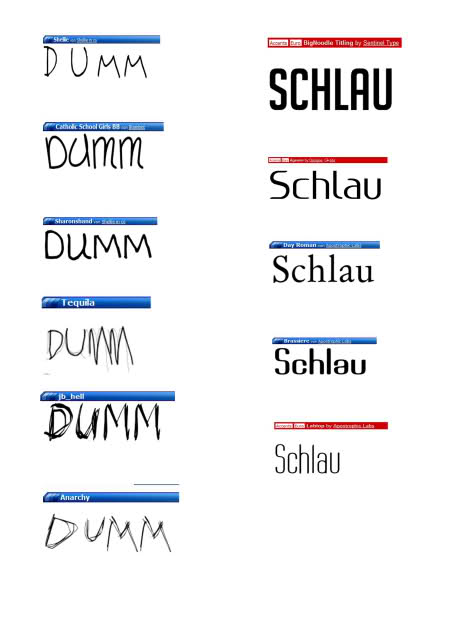
Dumm und Schlau - uniaufgabe - welche schriften?
hab zu morgen die aufgabe für die 2 wörter dumm und schlau die richtige schrift zu finden und die wörter dann in jeweils einem quadrat so anzuordnen das sie für sich und gegeneinander gut wirken.
ich hab nur einfach keine ahnung was ich am besten für schriften nehmen soll. besonders für schlau.
habt ihr eine idee?
für schlau evtl die vom duden? zumal ich nicht weiß welche das ist
ich hoffe ihr könnt mir noch so schnell helfen
für dumm nähme ich eine garamond (stempel wahrscheinlich), für schlau die comic sans.
comic sans ist ausgeschlossen weil das schriften sind die schon vorinstalliert sind und wir uns andere suchen sollen. und ne begründung dazu wäre ganz lieb.
ich muss noch nen blatt dazu schreiben warum ich diese schrift gewählt habe.
für dumm nähme ich eine garamond (stempel wahrscheinlich), für schlau die comic sans.
comic sans ist ausgeschlossen weil das schriften sind die schon vorinstalliert sind und wir uns andere suchen sollen. und ne begründung dazu wäre ganz lieb.
dann nimmste halt eine der milliarden alternativen zur comic sans. und die begründung ist die gegensätzliche aufladung der schriften unter typographen (der ich nicht bin, ich bin nur ein interessierter anwender, klugscheisser und konservativlinker anarchoaristokrat): garamond - gebildet, edel, traditionell, humanistisch, konservativ; comic sans: bild-zeitung, übernutzt, kindisch, verhasst, ...
ich muss noch nen blatt dazu schreiben warum ich diese schrift gewählt habe.
joa, aber du kannst nicht erwarten, dass hier irgendeiner deine hausaufgaben macht ;)
ne das weiß ich selber, hab ja auch schon gesucht und mir meine gedanken gemacht zu dem thema.
bin nur ne totale niete in typo.
und mit dem dozenten steh ich auch nicht so super.
mehr wie mir hilfe holen kann ich ja nicht :/
muss ja auf nen grünen zweig kommen
Für dumm würde ich in der Tat ebenfalls die Comic Sans nehmen. Die verwendet wirklich jeder, immer, überall. Da braucht man nur mal durch die Straßen zu laufen, echt zum heulen. Neulich habe ich sogar Geschäftspost in der Comic Sans erhalten.
Als schlau vielleicht irgendwas extrem konstruiertes, verkopftes.
Schlau ist nicht unbedingt das Gegenteil von dumm. Schläue kann letztendlich in Dummheit enden. Oder Dummheit wird durch schlaue Handlungen versteckt. Schläue ist kein Synonym für Klugheit oder Intelligenz, sondern eher für Durchtriebenheit, Diplomatie, Eigennutz usw.
So gesehen ist auch in der Schriftwahl nicht unbedingt Gegensätzlichkeit die Lösung.
Analysiere aus deiner Sicht die Begriffe und verzichte auf verbrauchte oder schlecht gemachte Schriften.
Schlau ist nicht unbedingt das Gegenteil von dumm. Schläue kann letztendlich in Dummheit enden. Oder Dummheit wird durch schlaue Handlungen versteckt. Schläue ist kein Synonym für Klugheit oder Intelligenz, sondern eher für Durchtriebenheit, Diplomatie, Eigennutz usw.
So gesehen ist auch in der Schriftwahl nicht unbedingt Gegensätzlichkeit die Lösung.
Analysiere aus deiner Sicht die Begriffe und verzichte auf verbrauchte oder schlecht gemachte Schriften.
so ähnlich hat sich mein dozent auch geäußert,
er sagte fast alle begriffe die er uns gegeben hat sind 2 deutig auszulegen
wir sollten uns die genaue definition raussuchen und uns slber gedanken machen. bei dumm und schlau ist auch durchtriebenheit mit drin und was genau ist dumm? unkenntniss oder einfach faul oder oder oder....
noch ein grund warum ich verzweifel.
aber eure tips sind schonmal super!!!
das hilft mir um einiges weiter.
danke!
für dumm nähme ich eine garamond (stempel wahrscheinlich), für schlau die comic sans.
… begründung ist die gegensätzliche aufladung der schriften unter typographen (der ich nicht bin, ich bin nur ein interessierter anwender, klugscheisser und konservativlinker anarchoaristokrat): garamond - gebildet, edel, traditionell, humanistisch, konservativ; comic sans: bild-zeitung, übernutzt, kindisch, verhasst, ...
Wie ’rum denn nun? :? (farbliche Hervorhebungen von mir)
Ansonsten war mein erster Gedanke, es genau anders herum anzugehen als in der ersten Skizze. Also:
DUMM ? eine Schrift, die »brutalstmöglich« daherkommt. Z.B. im Versalsatz, denn DUMME MENSCHEN SCHREIEN OFT, statt leise aber klug zu argumentieren. Der Hinweis mit der Bild geht schon in die richtige Richtung, ich denke aber an die Schrift des Logos (nur eben nicht condensed, sondern weitlaufend und heavy — Dumme dulden schließlich selten abweichende Meinungen; ihre Vorurteile sind wie in Stein gehauen).
Bei schlau fällt mir hingen zuerst eine Schreibschrift ein. Schreibschriften verbinde ich mit den Ideenskizzen von Ingenieuren, Naturwissenschaftlern, Architekten und Künstlern. Eine passende Schrift hätte natürlich nichts mit der Comic Sans gemein. Siehe sähe sehr schnell und flüssig geschrieben aus, vielleicht wie mit Bleistift oder (feiner) Kohle.
So gesehen ist auch in der Schriftwahl nicht unbedingt Gegensätzlichkeit die Lösung.
Analysiere aus deiner Sicht die Begriffe und verzichte auf verbrauchte oder schlecht gemachte Schriften.
Ein Schöner Einwand, Erwin! Da gewinnt die Aufgabe direkt an Subtilität und man muss nun ein wenig genauer darüber nachdenken. Warum für schlau nicht die Courrier und für dumm die Courrier bold?
Ich würde beide Begriffe in der Times New Roman schreiben – und bei dumm die beiden m vertauschen …
… hä?!